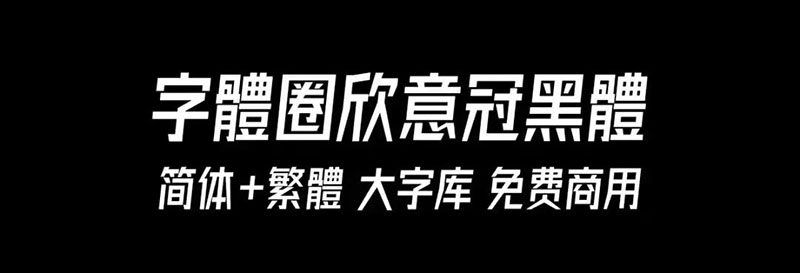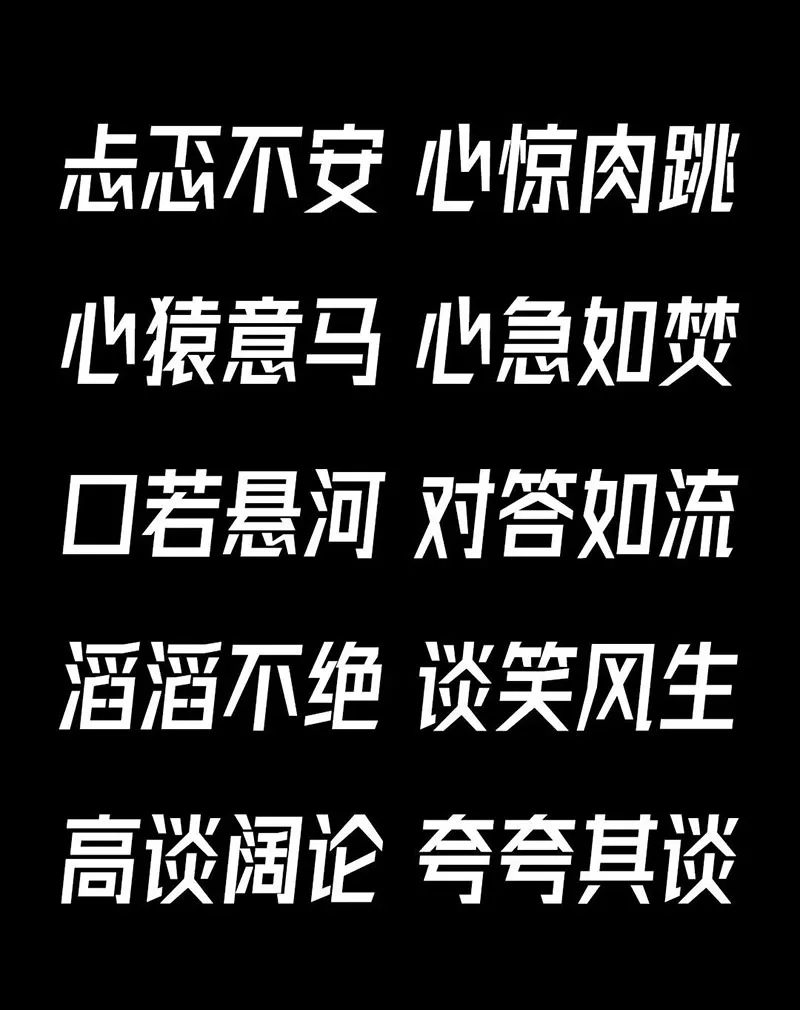
這套字叫《字體圈欣意冠黑體》,欣意=心意。對於這套字體的發佈,不希望只限於這是一套字體,我更想紀念一件事情,那就是今年的疫情。我想以我的專業技能為抗疫發聲,希望疫情能早點退去,早點讓祖國,讓世界恢復往日的繁華。
新增的漢字主要是對於港澳臺地區的國字標準,中文現總涵蓋9864字,現在的階段相對來說比較快了,很多字都有現成的字拿來拼,做起來還是比較輕鬆的。
4.0新增符號約200餘字符
去年有朋友跟我反映過沒有序號的問題,現在也補上來了。
4.0調整字母數字符號的字符間距
3.0默認的字母數字符號的字間距過於小了,看上去非常緊湊,而我們的中文卻比字母的間距大,所以就重新調整了一下。
4.0修改部分字形的細節。